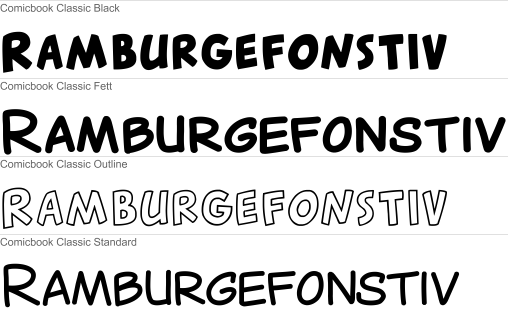
Wie mache ich Schriftschnitte vernünftig erkenntlich?
ich arbeite gerade an einem kleinen Comic-Projekt und habe mir dazu die Mühe gemacht, einen Font zu entwerfen, den ich für die Texte benutzen kann. Er sollte an die klassischen Comicschriften der 60er- und 70er-Jahre Marvel Comics angelehnt sein. Deshalb habe ich sie vorerst einfach mal "Comicbook Classic" genannt. Insgesamt habe ich vier Schriftschnitte.
Dabei habe ich aber zwei Probleme:
1) Ich tue mich ein wenig schwer damit, die Schnitte zu benennen. Standard und Fett sind die eigentlichen Schnitte für den Haupttext. Black und Outline sollen nur sporadisch benutzt werden. Kann man die so nennen, oder habt ihr da bessere Ideen? Man könnte die Black auch Fett nennen und die Fett dann Halbfett oder so ähnlich. Wonach richtet sich so eine Entscheidung? Ist das mir überlassen oder gibt es da ein paar Regeln?
2) Aus irgendeinem Grund ärgert mich Windows bei der Installation der Schriften. Auf dem Mac ist es gar kein Problem und alle vier Schnitte werden direkt als Teile von "Comicbook Classic" erkannt. Windows hingegen installiert die Schnitte quasi übereinander. Im "Fonts"-Ordner taucht nur eine Version auf; löscht man diese, erscheint die nächste. So ist auch nur immer die oberste Schrift in den Anwendungen zugänglich. Verrückterweise kommt dazu, dass Windows meint, "Comicbook Classic Black" als "Comicbook Classic Schwarz" anzuzeigen, obwohl ich die so nirgends genannt habe. Bei den anderen Schnitten wiederum setzt Windows ein "Mittel" hinter den Namen. Vielleicht kennt jemand einen Link à la "Fontinstallation unter Windows für Dummies"?
Generell, für Windoof musst du, nutzt du für alle 4 Schnitte den gleichen Familiennamen dann die Schalter für „Font is bold“ und „Font is italic“ nutzen. Wenn du für deeine Comic-Books die Textauszeichnung kursiv ohnehin nicht nutzen möchtst (wozu ja dann eigentlich auch entsprechend kursive Schnitte gezeichnet werden sollten, denn einfach nur schäg gezogen wirkt zumeist ohnehin falsch) kannsz du, wie ich dies für Spezialfonts auch mache, den Kursiv-Schalter auch missbrauchen. Dann könntest du denen normalen Schnitt als normal belassen, beim fetten setzt du sowohl den Schalter, als auch bei Style Name aud Bold. damit du dann den Black-Schnit genau so leicht nutzen kannst, und du ja ohnehin deine Schrift nutzt, könntest du diesen dann als „bold-italic“ markieren, und auch die entsprechenden Schalter setzen, und die Outline könnte dann deine kursive sein.
Icgh weiß, dieses Verfahren ist, mächtest du deine Schriften weiter geben, nicht ganz kosher, ist die Schriftart für den Eigenbedarf, ist das jerdoch sehr praktisch,m da du dann für deine 4 Varianten nur einmal sie Schriftart auswählen musst
Die beiden Schnitte Black und Outline hatten bei mir bislang keinerlei Kennzeichnung (weder fett noch kursiv), die anderen beiden entsprechend standard und fett. Deswegen sollte es eigentlich keine Überschneidungen geben.
Den Tipp von catfonts will ich mal als Notlösung im Hinterkopf behalten. Ich bin immer so pingelig, dass ich es doch gern direkt richtig hätte, aber für den Eigengebrauch müsste das ja eine einfache Lösung meines Problems sein.
Die beiden Schnitte Black und Outline hatten bei mir bislang keinerlei Kennzeichnung …
Eben! Das ist das Problem! Sie müssen eine Unterscheidung bekommen. Es darf keine zwei Schnitte einer einfachen Familie geben, die die gleichen Einstellungen für diese Felder haben. Sonst wird nur einer der Schnitte funktionieren.
WQenn ndu also die Variante mit dem misbrachtenm Kursiv, was in Windows schlicht den Zugriff erleichtert, nicht nutzen möchtst, dann müssen die Back, Outline (evtl weitere) dann die Unterscheidung im Familiennamen haben, da Windoof eben nur die 4 Standardvarianten einer Schrift als zusammengehörig akzeptiert, das letztlich auch aus Gründen der Abwqärtskompatibilität.
Danke Ralf, das hatte ich dann missverstanden. Ich habe direkt mal die installierten Schriften auf meinem PC angeschaut und entsetzt festgestellt, dass es keinen Font in mehr als vierfacher Ausführung gibt. Das war wohl ein typografischer Aha-Moment für mich. Ich muss also tatsächlich zwei Familiennamen angeben, wenn ich alle vier Schnitte unterbringen will ohne irgendeine "kursiv" zu nennen.
Allerdings habe ich mittlerweile den Eindruck, mein PC oder ich spinnen. Ich habe das Problem aufs Wesentliche reduziert und mich erstmal nur mit Std und Fett beschäftigt, schaffe es aber nicht mehr, beide gemeinsam zu installieren. An den Einstellungen der Fonts kann nun wirklich nicht mehr viel falsch sein - die eine ist klassifiziert als die Bold-Version der anderen. Ich lege mal eine Pause ein und versuche es später noch mal, durch Windows durchzusteigen ... *seufz*
…  schaffe es aber nicht mehr, beide gemeinsam zu installieren.
Dann nach dem Fontbenennungstipp gleich noch der zweite typische: Solange du »rumprobierst«, gibt jedem neuen Versuch einen neuen Familiennamen (»Meine Familie Beta5« etc.). Da die Fonts an verschiedenen Stellen zwischengespeichert werden, führt es ansonsten immer zu Problemen, wenn du versucht, neue Versionen auszuprobieren. Nur ein neuer Familienname garantiert, dass die Schrift wirklich systemweit als neue Version erkannt wird und in den Anwendungsprogrammen benutzt wird.
Und dann habe ich die 2 Schriften installiert, und mich gewundert, dass jetzt in c:windows\fonts nicht die zusätzlichwe Familie auftaucht, also öffne ich die als Stapel dargestellte Famile, und siehr da, diese enthält 6 Schriften, bei denen Windows die 2 Condensed-Schnitte als "Schmal" bezeichnet. "Schmal" kommt aber gar nicht in den internen Bezeichnungen der Schriftart vor.
In der Anwendung allerdings erscheinen die 2 zusätzlichen Schnitte dann alerdings als eigene Familie., im Windows-Editor dagegen ist es eine Familie